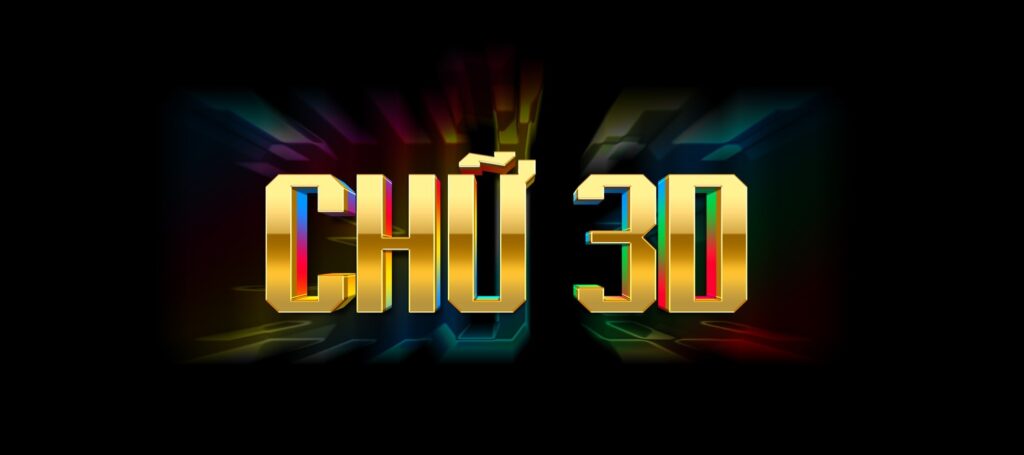
Font chữ 3D là nhóm phông chữ đặc thù mô phỏng khối hình học ba chiều với các góc nghiêng trục đo, hiệu ứng kéo khối nổi và các mảng đổ bóng thị giác sống động ngay trên bề mặt phẳng. Sở hữu chiều sâu không gian chân thực và sức mạnh thị giác vượt trội, font chữ 3D đẹp là chất liệu trực quan tuyệt vời để các kiến trúc sư, nhà thiết kế hoàn thiện các bản vẽ phối cảnh mặt tiền showroom container, thiết kế chữ nổi biển hiệu tòa nhà hay các ấn phẩm đồ họa sự kiện mang phong cách hiện đại.
Khối hình đa chiều và hiệu ứng đổ bóng thị giác của font chữ 3D
Điểm cuốn hút của phông chữ 3D nằm ở khả năng biến đổi các ký tự văn bản thông thường thành những khối kiến trúc thu nhỏ có đầy đủ góc nhìn, diện sáng và diện tối. Cấu trúc chữ sở hữu các đường vát cạnh sắc nét, phần đổ bóng kéo dài có chủ đích mô phỏng hướng chiếu của nguồn sáng tự nhiên, mang lại cảm giác các con chữ như đang nổi lên khỏi mặt tường công trình.
Sự ổn định về mặt thị giác của dòng font này giúp thông điệp truyền thông trở nên sống động, dứt khoát và thu hút sự chú ý tức thì từ phía người nhìn. Khi xuất hiện trên các bề mặt vật liệu kiến trúc hiện đại như vách tôn sóng container, tấm alu gương xước hay tường bê tông mài trong các công trình nhà lắp ghép thế hệ mới, kiểu chữ 3D đẹp tạo nên điểm nhấn kiến trúc giàu năng lượng.
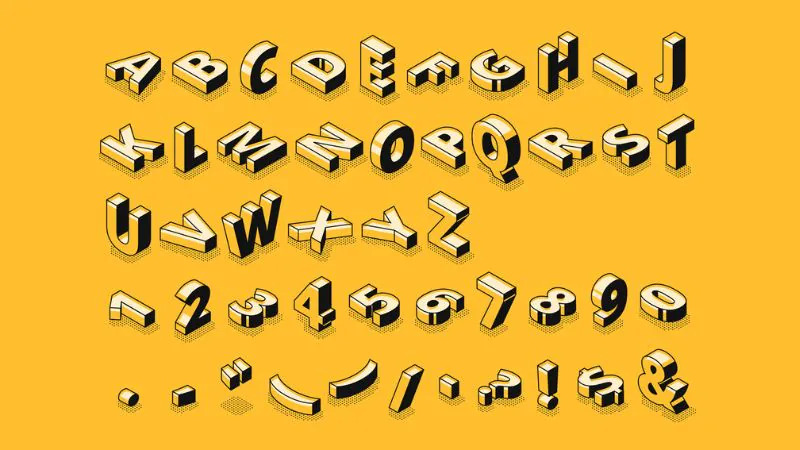
Tư vấn từ chuyên viên: Font chữ 3D sở hữu cấu trúc hình khối rất dày và có độ chiếm dụng không gian lớn. Để bản thiết kế đạt hiệu quả thẩm mỹ tốt, bạn nên sử dụng phông chữ này cho các tiêu đề chính, tên tòa nhà hoặc các con số dự án ở kích thước lớn.
03 Ứng dụng font chữ nổi 3D vào công trình thực tế
Nhờ chiều sâu không gian ấn tượng và tính kết nối cao với kỹ thuật gia công biển bảng, bộ phông chữ này mang lại giá trị thực tế lớn trong khâu hoàn thiện các công trình hiện đại:
- Hệ thống chữ nổi mặt tiền cho Văn phòng Container và Showroom: Những khối chữ của font chữ nổi 3D rất ăn ý khi gia công uốn chân bằng inox xước, mica hút nổi hoặc tôn sơn tĩnh điện gắn đèn LED hắt sáng chân, giúp mặt tiền công trình toát lên vẻ bề thế và sang trọng cả ngày lẫn đêm.
- Phối cảnh phối cảnh kiến trúc 3D: Sử dụng phông chữ ba chiều để đặt tên dự án trực tiếp lên các khối nhà trên phần mềm đồ họa giúp khách hàng và chủ đầu tư dễ dàng hình dung sự tương quan tỉ lệ giữa công trình và bộ nhận diện thương hiệu.
- Bảng chỉ dẫn định hướng và Tên phân khu dự án: Phông chữ này khi gia công bằng kim loại tấm dày hoặc đúc khuôn bê tông trang trí sẽ giúp các khu vực chức năng trong khu đô thị lắp ghép trở nên nổi bật và dễ định vị từ cự ly xa.
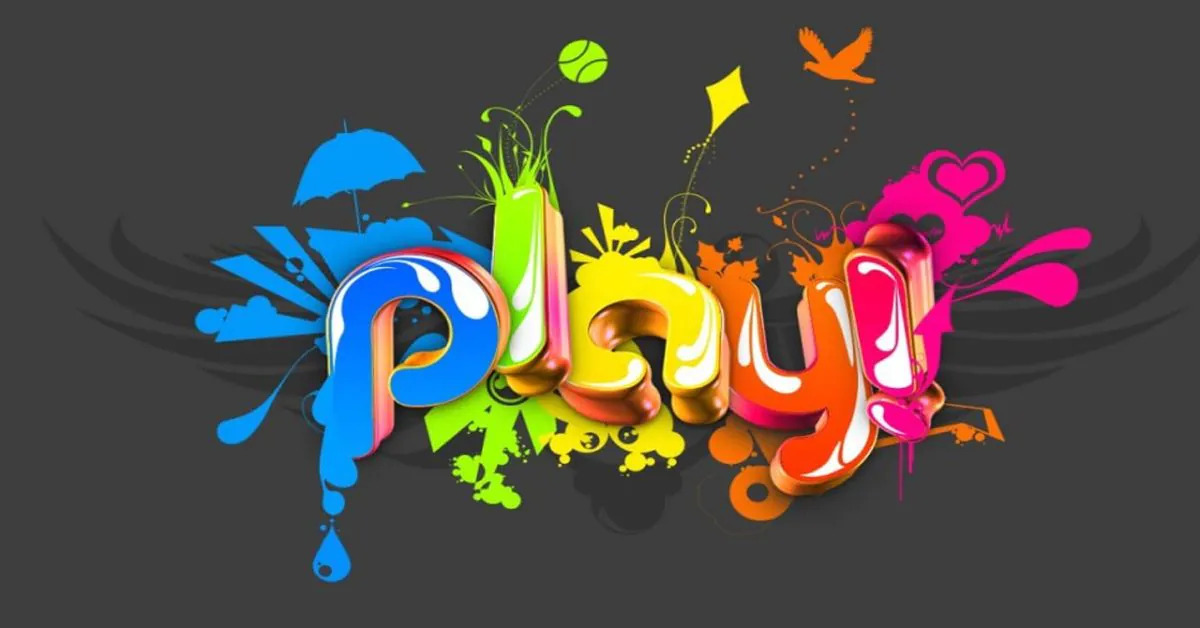
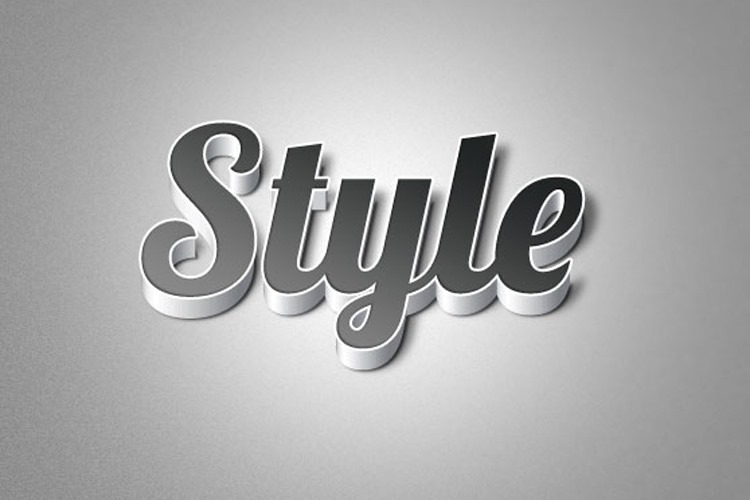
03 Lưu ý bố cục kiểu chữ 3D đẹp giữ trọn độ sâu phối cảnh
Để khai thác hiệu quả vẻ đẹp của dòng font ba chiều này mà không gây cảm giác rối mắt cho bản vẽ, người thiết kế nên lưu tâm một số kinh nghiệm sau:
- Đồng bộ hướng chiếu sáng: Khi trình bày chữ 3D trong phối cảnh công trình, bạn cần điều chỉnh góc đổ bóng của phông chữ trùng khớp với hướng nắng tự nhiên trong bản vẽ 3D để đảm bảo tính chân thật của không gian.
- Nới rộng khoảng cách ký tự: Do chữ 3D có phần thân khối kéo dài sang bên hoặc xuống dưới, các ký tự rất dễ chạm vào nhau. Bạn nên kéo giãn nhẹ khoảng cách giữa các chữ cái để các mặt vát nổi được hiển thị trọn vẹn.
- Phân biệt màu sắc giữa mặt chữ và diện nổi: Hãy chọn màu mặt chữ sáng hơn phần khối kéo dài (hoặc ngược lại) để tạo độ tương phản rõ rệt, giúp các cạnh viền sắc sảo của hình khối được tôn vinh rõ ràng.
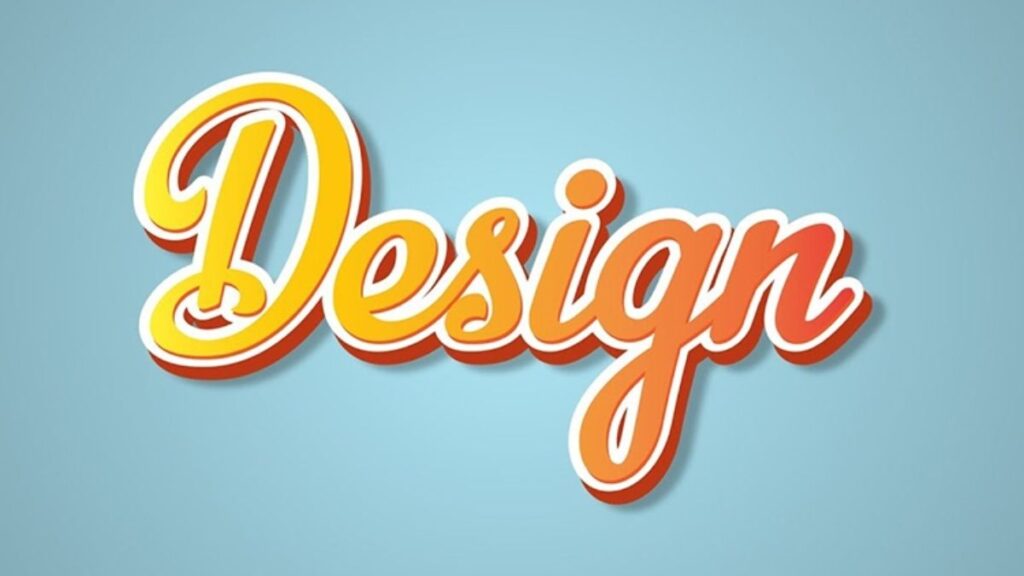
FAQs – Thắc mắc thường gặp khi sử dụng phông chữ 3D